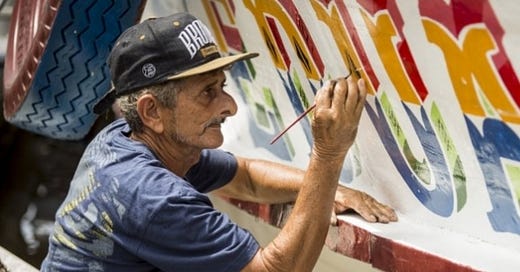
Tipo Aquilo #45 – Letras que flutuam
Para o povo do rio, o barco é muito mais do que um meio de transporte. O ribeirinho depende de sua embarcação para alimentar e sustentar a família, viajar, cumprir suas obrigações com seus pares, conviver em comunidade e ter contato com outros lugares. Quando você mora num lugar em que a economia gira em torno do rio, o barco torna-se uma segunda casa, uma extensão do lar. A relação é mais profunda do que apenas uma relação de uso: uma família pode viver do sustento trazido pelo barco por várias gerações, e do mesmo jeito que decoramos nossa casa para que ela projete as coisas com que nos importamos e o status perante a sociedade, o capitão também faz do aspecto visual do barco uma projeção do que ele considera visualmente bonito e de quem ele é para a sociedade.
Os abridores de letras, que convivem junto aos calafates, fazem com que a identificação textual dos barcos não se limite à dizer qual embarcação é qual. O modo com que as letras são pensadas, desenhadas e decoradas diz sobre como as pessoas daquela região entendem a função das letras, sobre quem é e qual é o status social do dono do barco, e sobre toda a cultura à beira do rio. Carimbó, tecnobrega, um cristianismo ainda apegado ao folclore e os costumes dos povos indígenas; essas e outras influências estão presentes nas formas e cores utilizadas pelos pintores das embarcações das cidades banhadas pela baía do Marajó, no norte do Pará. A tradição dos abridores de letras de barcos, documentada pela Prof. Fernanda Martins, é o nosso tema de hoje.
Como uma forma legal de começar pelo começo, o termo “abridor de letras” pode soar estranho pra muita gente. No nosso cotidiano, as letras surgem pela impressão numa superfície por tinta ou luz, ou pelo ato de escrever, usando algo que marque uma superfície com gestos contínuos ou intermitentes. “Abrir” uma letra não é comum para nós, mas na tradição da tipografia, “abridor” era um termo análogo ao gravador ou ao “escultor” de letras, por assim dizer, que utilizava ferramentas muito precisas para criar as formas nas matrizes metálicas que, posteriormente, eram moldes para a fundição de tipos móveis. Nos dias atuais, muito poucos no mundo ainda criam letras assim, mas a denominação permaneceu e foi adquirida por quem cria letreiros, placas e todo tipo de superfície em que se deseja letras com pincel e tinta, de forma que nenhuma técnica de impressão consiga oferecer o mesmo sabor.
Uma amostra do uso desse termo é outro projeto de documentação da sabedoria popular de desenhar letras decoradas, o dos abridores de letras de Pernambuco, das Profs. Fátima Finizola e Solange Coutinho. Tal como no Pará, o registro gráfico da atuação desses abridores ajuda essa cultura a ganhar notoriedade e longevidade na memória gráfica brasileira. Ambas têm pontos em que conversam com a tradição tipográfica de criar letras destacadas e ornamentadas, mas que distanciam-se ao conversar com as culturas locais e tomar delas as influências para o uso de formas, cores, contrastes e outros elementos. No caso dos abridores de letras da baía do Marajó, os barcos são a grande vitrine dessas letras decoradas.
A decoração das letras varia de acordo com o gosto e o bolso do cliente; encomendadas pelo dono do próprio barco, ou pelo estaleiro responsável, os abridores atuam junto aos calafates, que trabalham na construção e reparo das embarcações. Quando o barco está finalmente n’água, esses abridores tomam as medidas da área a ser pintada, os dizeres que preencherão o espaço e, com instrumentos de medida e guia, começam a riscar os contornos que serão preenchidos com tinta e os espaços alocados para cada cor ou efeito de transição de cores. À medida que os abridores de letras ganham experiência, deixam para trás a necessidade de rascunhar cada traço, ganhando mais agilidade e expressividade no desenho das letras.
O preenchimento começa com pelo menos duas cores contrastantes que separam as metades de cima e de baixo das letras. Essas letras, quase sempre maiúsculas, possuem floreios e serifas ornamentais, chamadas de Toscanas, que eram comuns nos séculos XVIII e XIX em impressos efêmeros e capas de livros. Depois, vem o “caqueado”, os adornos às camadas iniciais, como sombreados, extrusões e outras pinturas decorativas. Esse caqueado, também dividido em duas partes, demanda um novo conjunto de cores que ofereçam contraste entre si e entre as camadas iniciais. É no caqueado que aparecem os efeitos com transição de cor, em sombras de extrusões (quando a letra fica “em 3D”), e também aparecem riscos e desenhos, como pequenas hachuras, que embelezam as letras no final do trabalho.
Abrir letras em uma embarcação demanda de até uma dezena de cores diferentes de tinta, e o resultado é um produto altamente colorido e decorado. Esses ornamentos são um espaço em que os abridores de letras “competem” entre si, buscando fazer letreiros “mais bonitos que o outro” baseados nos barcos que vêm e vão rio adentro. O trabalho dos abridores de letras não se resume aos nomes dos barcos; eles encarregam-se também de escrever em coletes salva-vidas, boias, registro de inscrição estadual em cabines, e outros dizeres, geralmente religiosos. Elas também estão presentes em fachadas comerciais, faixas de festas populares e outros letreiros, e recentemente têm ganho o auxílio da pistola de ar comprimido para pinturas mais rápidas e com mais misturas de cores.
O aprendizado desse ofício passa entre abridores de maneira informal; não há uma escola voltada para o ensino da confecção de letras, como acontece entre cartazistas, por exemplo. As formas das letras e os estilos de decoração são transmitidas entre gerações ou aprendidas de forma autodidata, por observação e reprodução. Isso distancia os abridores de letras das normas da tipografia, mas confere uma aproximação muito maior com a cultura ribeirinha, dando identidade à letra decorativa amazônica. Essas letras dialogam com expressões gráficas vistas em outros lugares, como no Peru, Colômbia e Venezuela, que também vêm da sabedoria e interpretação popular das formas das letras.
As etapas Belém e Marajó do projeto, registradas nos documentários “Letras Q Flutuam” e “Marajó das Letras”, trazem para o Brasil uma mostra dessa cultura das letras decoradas, com as histórias dos abridores, a prática da confecção das letras e a transmissão desse conhecimento para outras gerações de artistas ribeirinhos. Por mais que certos elementos tenham origem na Europa, a América Latina dá o seu jeito de reinventar e usar esses adornos e formas de uso de um jeito novo, que carregam consigo o sabor dos pratos típicos, os ritmos locais, as cores vivas da natureza, e tudo que faz um bom pintor, “aquele que num pequeno espaço, consegue fazer uma grande coisa”.
Recomendações:
🎧 Podcast: O que é Carimbó?, episódio do podcast Diáspora a cor da nossa cultura, produção da N’kinpa, sobre a história e tradição do Carimbó.
🎥 Vídeo: Letras que Flutuam – Etapa Belém o documentário curta-metragem de registro do ofício dos abridores de letras do Pará, com foco em Belém e cidades vizinhas.
🔗 Link: Letras Q Flutuam, o site oficial do projeto de documentação e registro dos abridores de letra da região do Marajó.